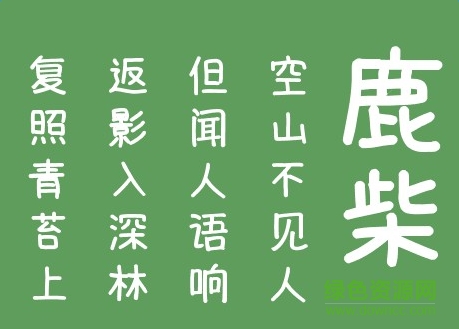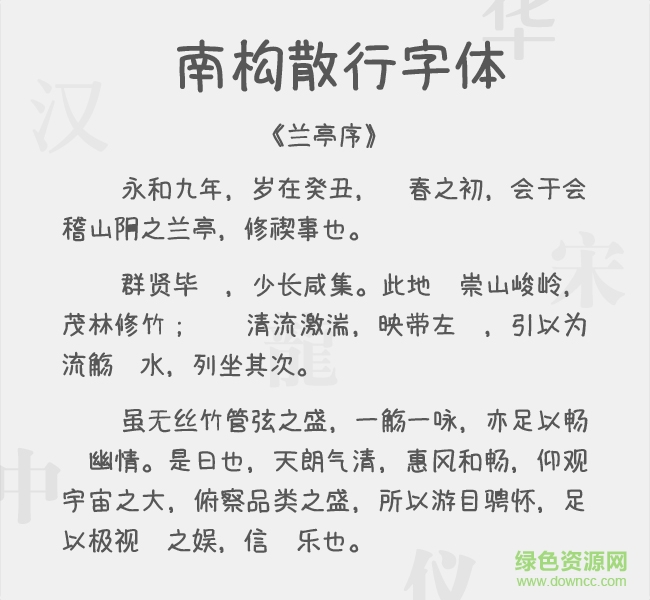
南構(gòu)散行字體
南構(gòu)散行字體是一款免費(fèi)的南構(gòu)字體,該字體雅致大氣,韻味十足,看上去生動(dòng)又散漫,可用來(lái)表現(xiàn)手寫(xiě)詩(shī)文或藝術(shù)設(shè)計(jì),喜歡的朋友快來(lái)綠色資源網(wǎng)下載吧!
南構(gòu)散行字體